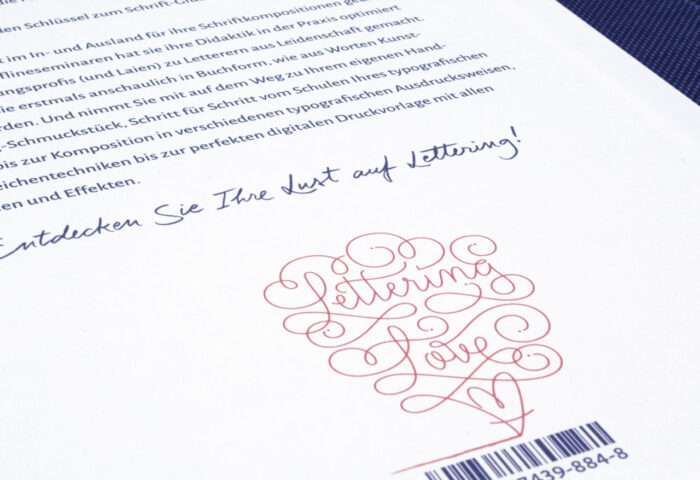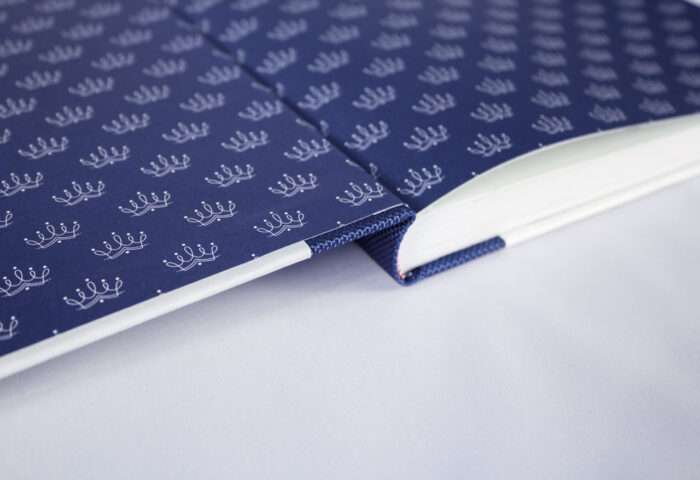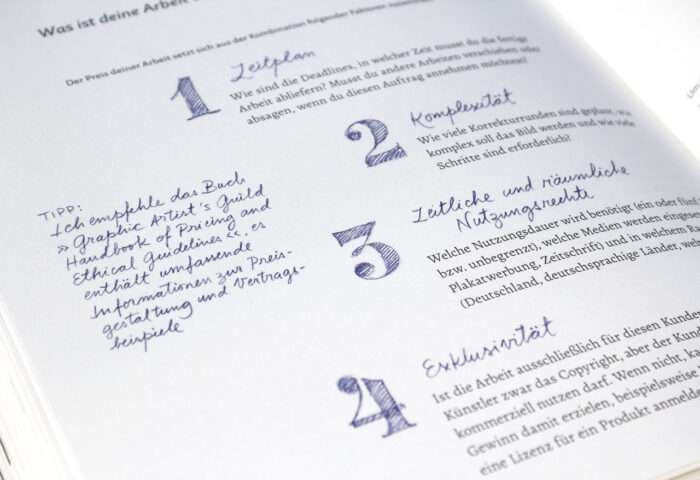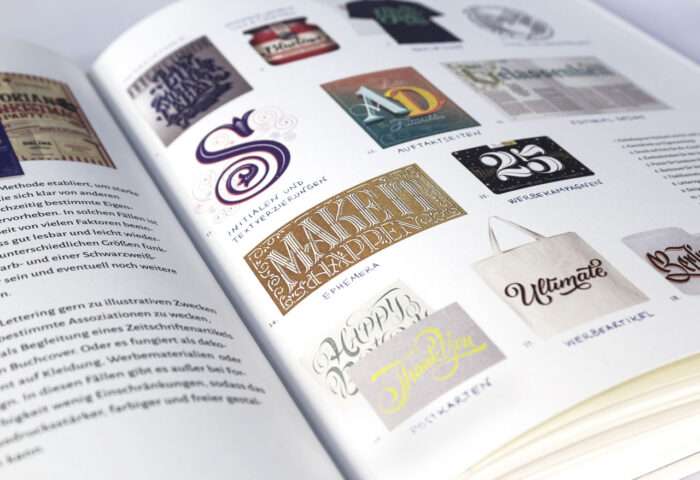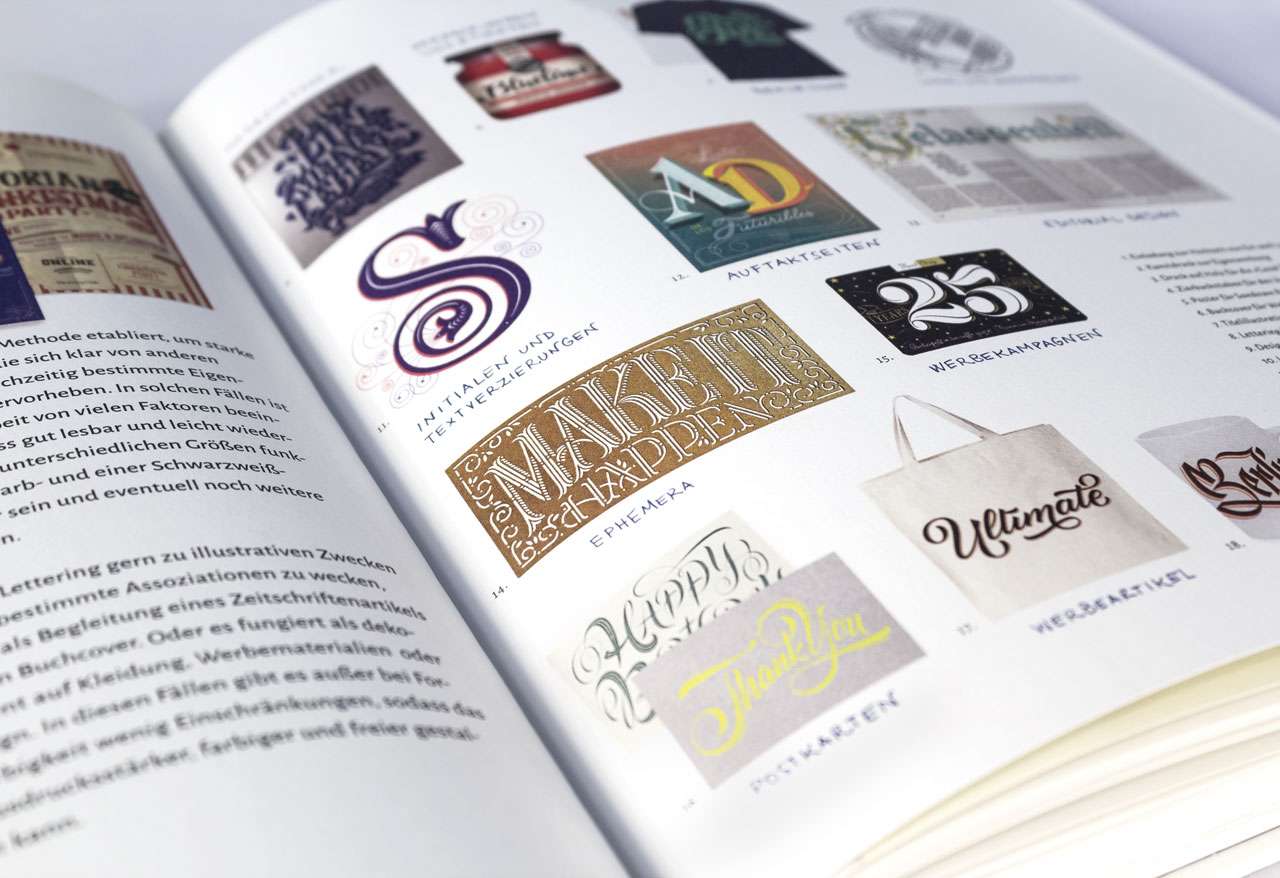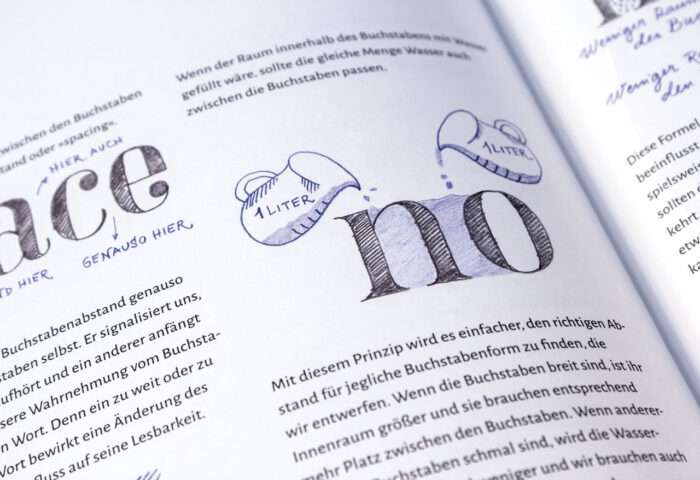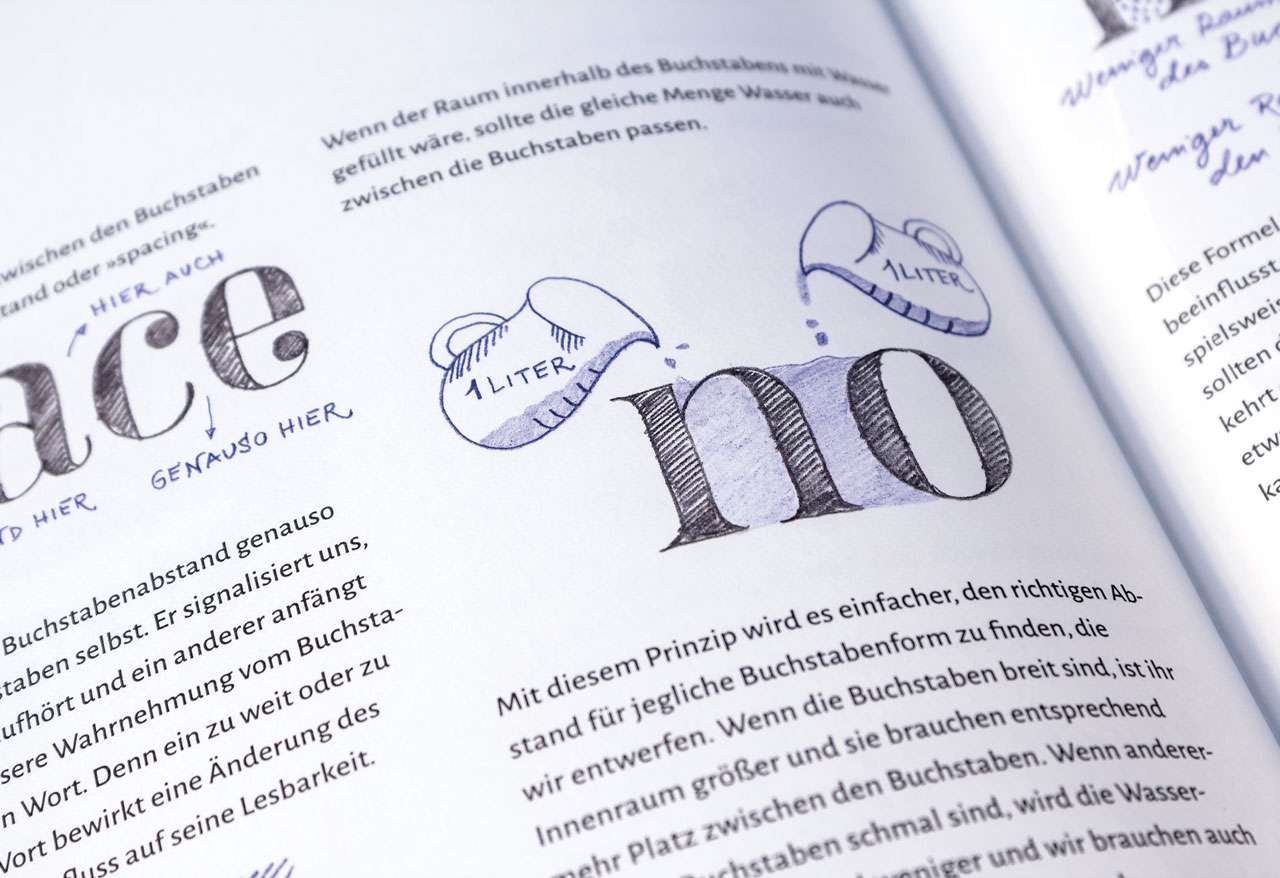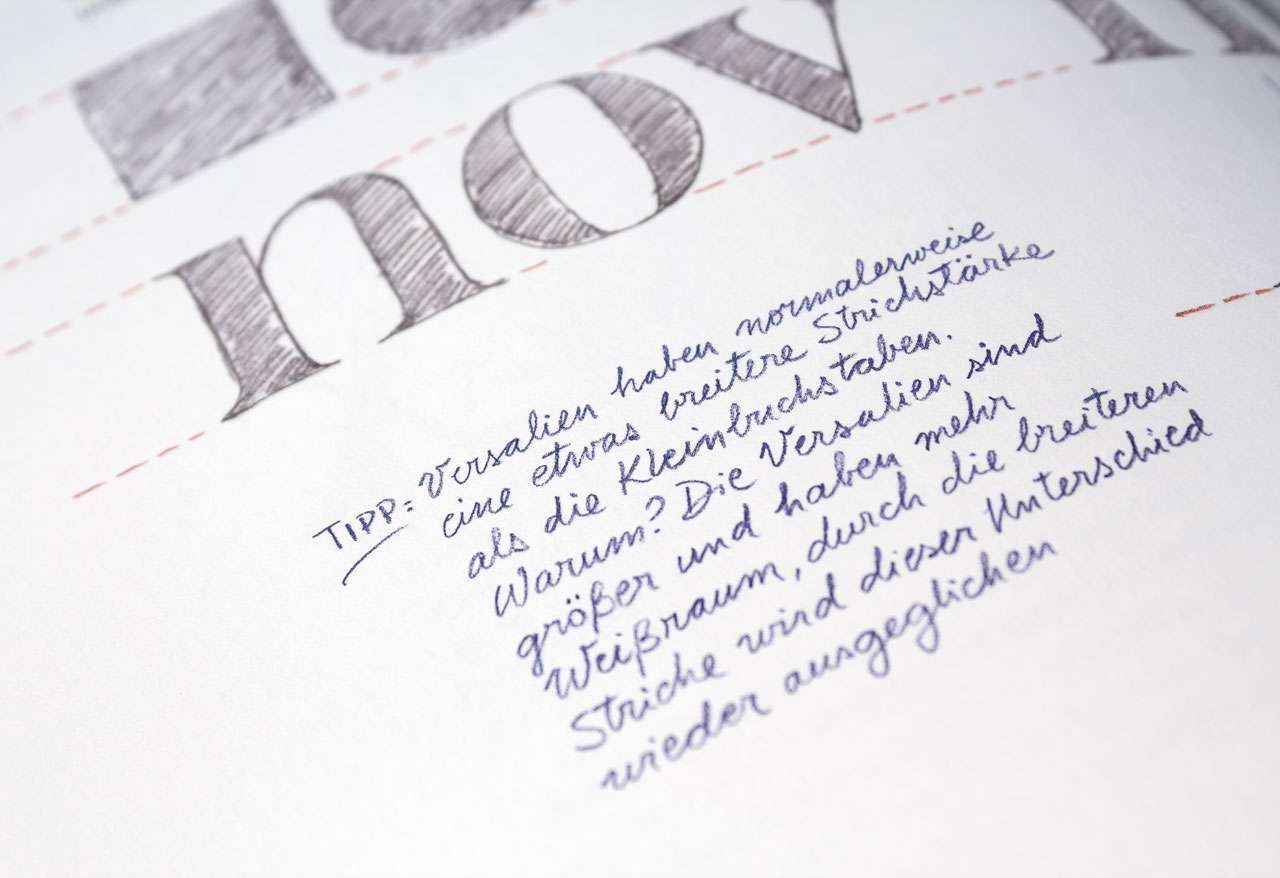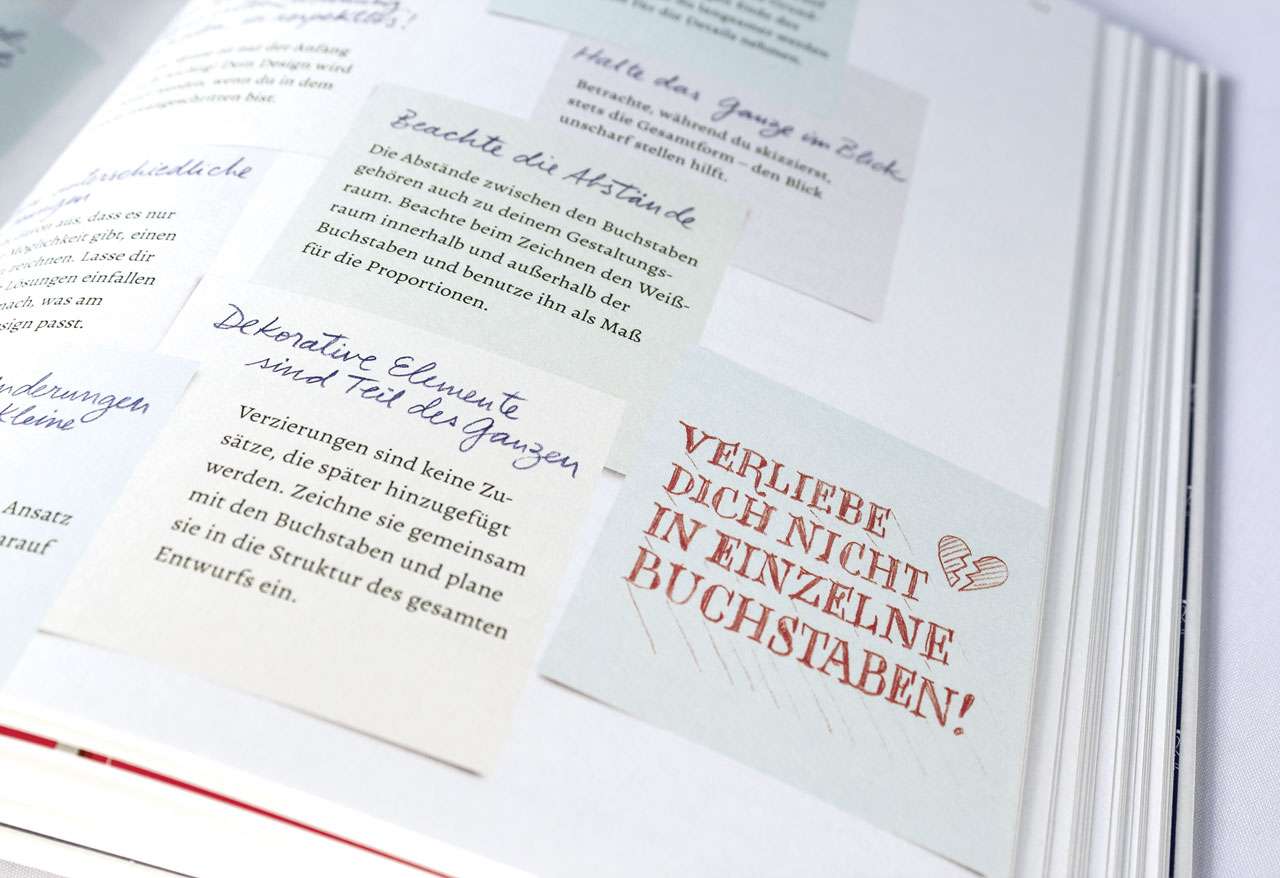
Konzepte, Werkzeuge und Techniken, die Sie auf dem Weg zu Ihrem ganz eigenen Lettering-Stil begleiten!
Begeistert beobachten Sie Handlettering auf Schiefertafeln, Plakaten, Covern und Hochzeitskarten? Sie haben auch schon ein wundervolles Paperblank gekauft und das wartet nun in der Schublade? Aber irgendwie fehlt bislang der entscheidende Impuls, ein Workshop, der Sie Schritt für Schritt begleitet, Ihre Lust auf Lettering weckt und Sie mit Freude zum Ziel führt?
Martina Flor wird im In- und Ausland für ihre Schriftkompositionen gefeiert und gebucht. In On- und Offlineseminaren hat sie ihre Didaktik erprobt und Gestaltungsprofis und Laien zu Letterern aus Leidenschaft gemacht. Hier zeigt sie erstmals in Buchform, wie aus Worten Kunstwerke werden. Und nimmt Sie mit auf den Weg vom Schulen Ihres typografischen Auges bis zum ausdrucksstarken Ausleben Ihrer Lust auf Lettering.
Warum keine Übungsseiten?
Wir glauben, dass Sie Ihre Praxisübungen da machen, wo Sie das wollen. In eine Kladde, ein Paperblanc, ein visuelles Tagebuch oder auf Papier, das Sie danach durchaus auch mal wegwerfen. Und dass ein Übungsblatt im Buch genau das Gegenteil von dem macht, was Martina Flor will: nämlich nicht locker.
Warum vermittelt dieses Buch auch Grundlagen der Typografie?
Auch, wenn Lettering für Sie erstmal aus der Lust am Machen heraus reizvoll ist oder Sie Entspannung dabei suchen (und finden), verstehen wir uns als Ihr professioneller Begleiter. Und dann kann man Handlettering nicht losgelöst von den Gesetzen und Erkenntnissen der Typografie und visuellen Kommunikation sehen. Ihre Arbeiten bleiben individuell-kraftvoll und sie werden dennoch einem bestimmten Profistandard genügen, weil Sie Gesetzmäßigkeiten der Typografie by the way mitgenommen haben.
Warum so wenige schöne Stilvorlagen?
Martina Flor sieht das Buch als Startblock für Ihren individuellen Ausdruck, sie gibt Ihnen Konzepte, Werkzeuge und Techniken an die Hand, sie präsentiert den Weg, den sie selbst geht und nicht fertige Projekte (auch wenn die absolut präsentationswürdig sind!). Sie will Ihre Lust am eigenen Lettering-Ausdruck wecken und glaubt an Ihre Kreativität.
Lust auf Lettering
Ein praxiserprobter Workshop in zehn Schritten
Tipps und Tricks
Fadengehefteter Festeinband aus leuchtblauem foliengeprägten Leinen und hochwertigem, bedruckten Papierüberzug